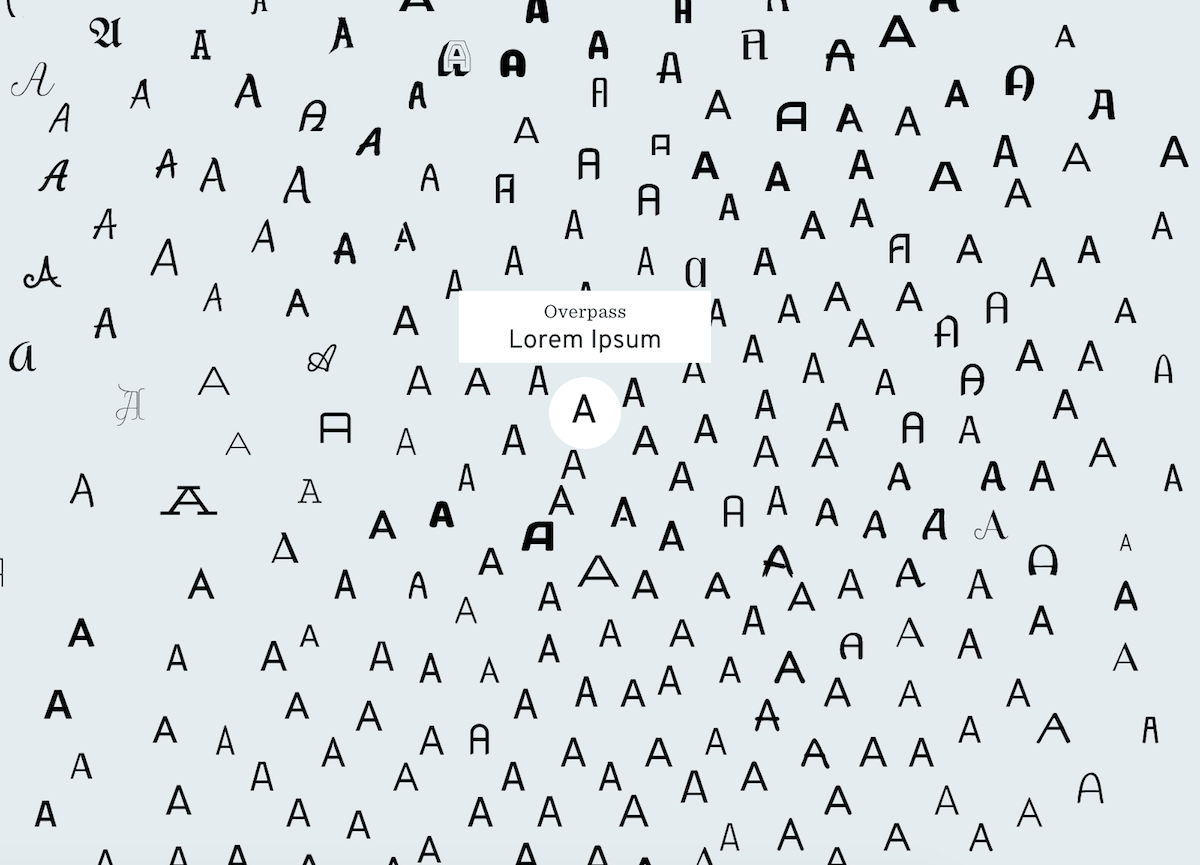
Melihat jenis font yang begitu banyak bisa bikin pusing kepala. Tapi ketika teknologi artificial intelligence mengambil alih, hal itu jadi pengalaman luar biasa.
Itulah yang berusaha diwujudkan oleh tim IDEO. Mereka mengumpulkan lebih dari 750 font, mengembangkan analisis dengan bantuan neural network, dan menampilkannya dalam bentuk peta di bidang dua dimensi. Hasilnya adalah Font Map.
Eksperimen ini berawal dari tantangan yang dihadapi tiap perancang grafis, yaitu menentukan font untuk proyek mereka. Seringkali font yang dipilih hanya itu-itu saja. Perancang grafis perlu sebuah cara untuk menemukan alternatif atau variasi font lain dengan mudah. Demikian penjelasan Kevin Ho, software designer dan project lead IDEO, di artikel blog-nya.
Font Map menampilkan bidang pencarian beserta beberapa alternatif font di sebelah kiri layar. Sedangkan di sebelah kanan, terdapat sejenis peta yang menampilkan huruf A dalam berbagai jenis font.
Tampilan berbagai jenis font di Font Map ini terlihat acak. Ada sans serif, serif, script, dll bergabung jadi satu. Sekilas, hubungan di antara font itu tidak nyata.
Kita bisa menggunakan bidang pencarian di sidebar kiri untuk memasukkan nama salah satu font (yang kita kenal). Nanti, akan muncul saran font sejenis di bawahnya, dan peta di sebelah kanan akan menunjukkan posisi font tersebut.
Kalau mau, kita juga bisa menelusuri font langsung di peta. Klik salah satu huruf A untuk melihat nama font tersebut. Sisanya sama seperti proses di atas. Akan muncul beberapa alternatif font sejenis di sidebar kiri.
Apakah hasilnya seperti yang diharapkan?
Mungkin tidak ada jawaban yang tepat. Tiap designer punya kekhasan masing-masing. Cara ini belum tentu sesuai dengan gaya mereka. Apalagi jumlah font yang ada di internet juga jelas lebih dari 750.
Toh, proyek Font Map ini masih disebut sebagai eksperimen. Ini berarti proyek ini bisa berkembang lagi. Apalagi kita bicara soal artificial intelligence.
Saya membayangkan nantinya Font Map bisa hadir dengan spesifikasi yang lebih jelas. Misalnya menentukan memilih jenis font untuk judul, atau kategori tulisan lain. Dengan demikian bisa digunakan dengan lebih praktis.